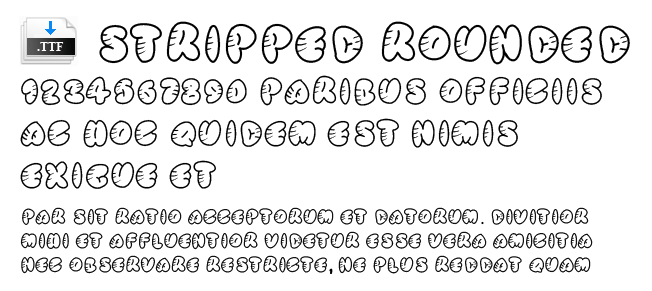
Stripped Rounded .ttf | Police gratuite
Voici une police de caractère Cartoon, qui existe aussi dans deux versions un peu différentes - je les mettrai en ligne prochainement. A utiliser sans modération !